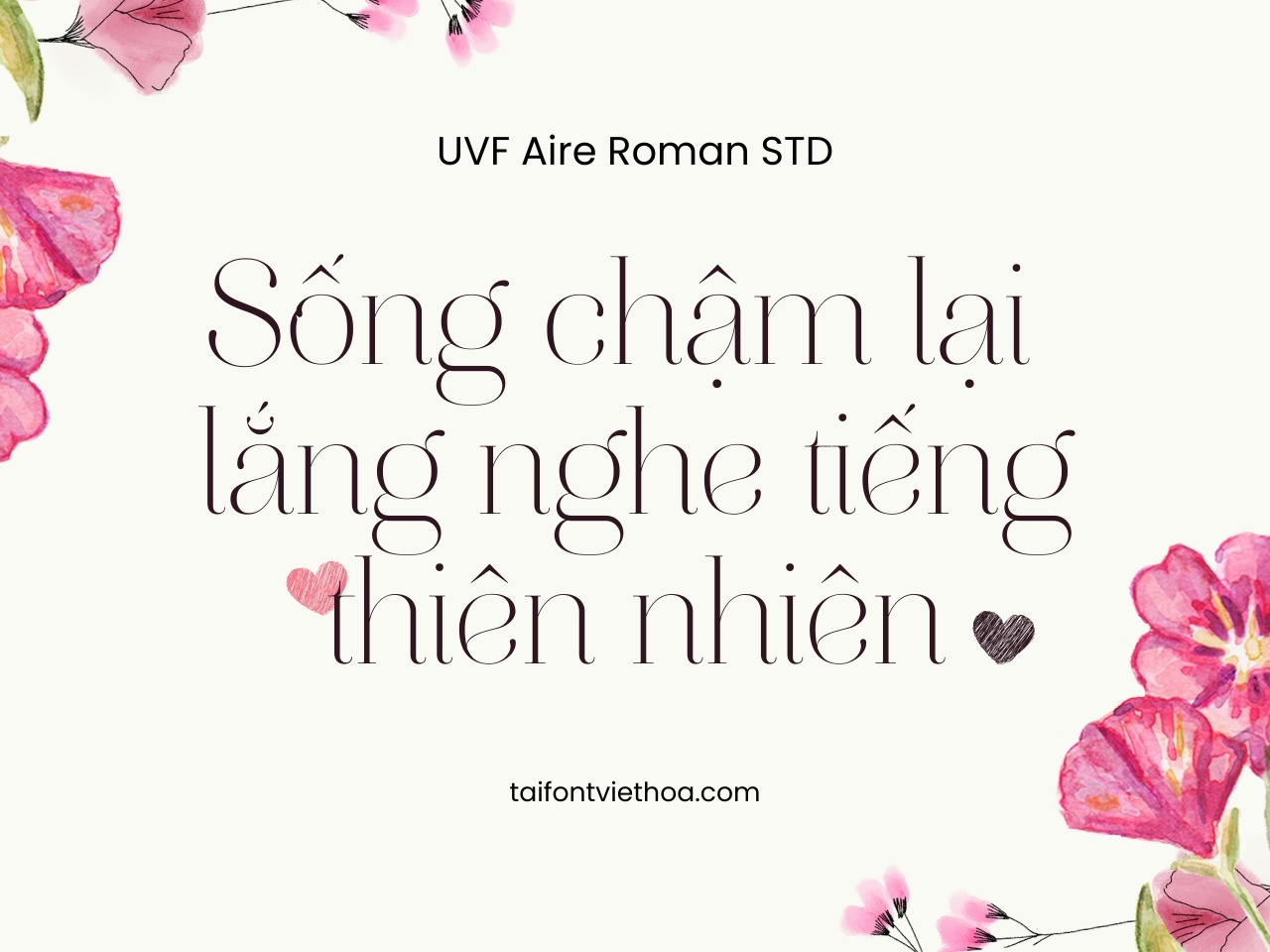
Font việt hóa UVF Aire Roman Std
Giới thiệu về font UVF Aire Roman Std
UVF Aire Roman Std là một phông chữ serif mang phong cách cổ điển thanh lịch, được thiết kế nhằm truyền tải sự tinh tế, trang trọng nhưng vẫn giữ được sự mềm mại trong từng nét chữ. Phiên bản “Roman Std” của dòng font Aire này đặc biệt thích hợp cho thiết kế biên tập, ấn phẩm in ấn hoặc thương hiệu mang phong cách cao cấp. Font đã được sưu tầm và chia sẻ bởi thành viên Font Chuẩn, và được taifontviethoa.com sử dụng trong nhiều dự án liên quan đến biên tập, sách báo và hệ thống nhận diện thương hiệu trang nhã.
Đặc điểm thiết kế và ứng dụng của UVF Aire Roman Std
UVF Aire Roman Std nổi bật với các chân chữ mảnh, đầu nét sắc sảo và độ tương phản giữa nét dày – mảnh rõ rệt, tạo nên sự nhấn nhá tự nhiên và sang trọng. Cấu trúc chữ cân đối, dễ đọc, phù hợp cả trên tiêu đề lớn và nội dung văn bản. Với khả năng hỗ trợ đầy đủ tiếng Việt, font hoạt động tốt trên cả nền tảng in ấn truyền thống lẫn kỹ thuật số.
Ứng dụng lý tưởng: tạp chí thời trang, bìa sách chuyên đề, nhận diện thương hiệu cao cấp, tài liệu quảng bá cho mỹ phẩm hoặc ấn phẩm nghệ thuật. Ngành nghề phù hợp: xuất bản, thời trang, mỹ phẩm, thiết kế nội dung cao cấp và truyền thông thương hiệu.